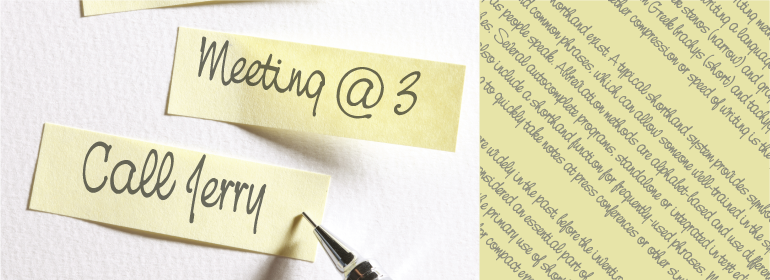
Nevison Casual
Nevison Casual,这款字体结构工整、笔画清晰,兼顾美观与易读性,适用于标题、正文、海报、包装、LOGO 等多种场景。字形优雅稳定,风格百搭耐看,适配日常排版与创意设计,让文字呈现更舒适、更具质感。Nevison Casual一笔一画,皆是细节,以均衡的比例、流畅的线条打造舒适视觉体验,字形端正大气,风格简约现代。无论是商业设计、品牌宣传还是日常排版,都能轻松驾驭,让文字更有格调与力量。Nevison Casual字体下载。